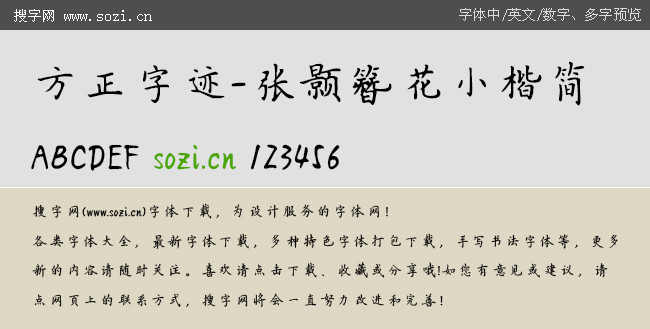
方正字跡-張顥簪花小楷簡(jiǎn)
搜字網(wǎng)提供一款方正字跡-張顥簪花小楷簡(jiǎn)中文字體下載,方正字跡-張顥簪花小楷是一款非常漂亮的藝術(shù)字體,字體看上去非常的靈動(dòng)、飄逸,它的形狀若簪花,雅致娟麗,適合應(yīng)用于藝術(shù)設(shè)計(jì)、廣告宣傳設(shè)計(jì)、網(wǎng)頁(yè)信息展示、書(shū)法字帖等,廣泛用于各種書(shū)刊、畫(huà)冊(cè)的設(shè)計(jì)、報(bào)紙和雜志和書(shū)籍等領(lǐng)域。
- 風(fēng)格類(lèi)別: 手寫(xiě)書(shū)法體